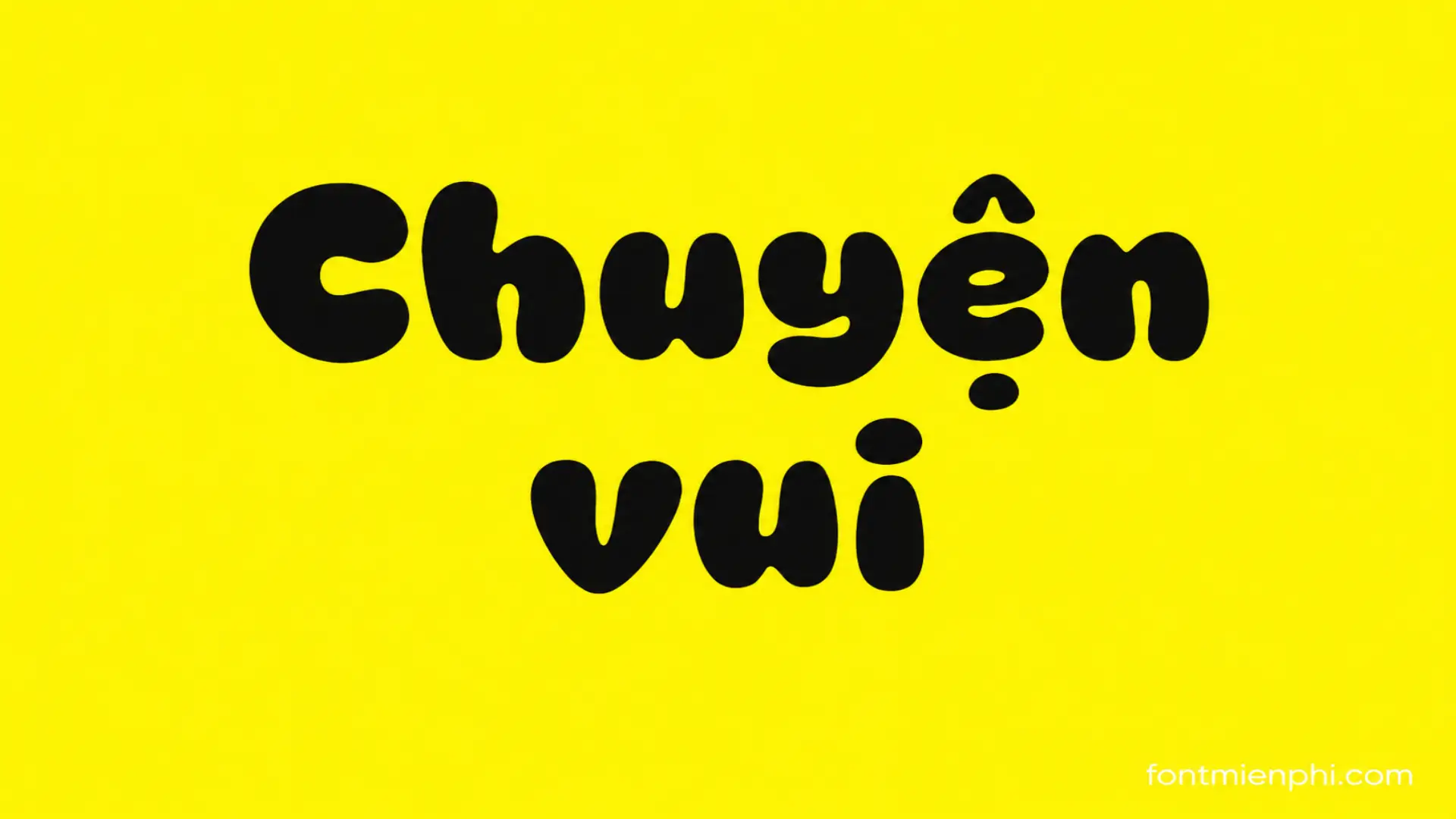
Tải Font Việt Hóa 1FTV VIP Super Kidpop – Phông Chữ Bầu Bĩnh, Siêu Dễ Thương Cho Thiết Kế
Chào mừng bạn đến với Fontmienphi.com! Nếu bạn đang tìm kiếm một phông chữ mang đậm nét trẻ trung, đáng yêu để “thổi hồn” vào các dự án thiết kế thì Font Việt hóa 1FTV VIP Super Kidpop chính là chân ái. Với phong cách to béo, ngộ nghĩnh, đây hiện là một trong những bộ font được giới Designer săn lùng và ứng dụng rộng rãi nhất.
1. Điểm nổi bật của Font Việt Hóa 1FTV VIP Super Kidpop
Không phải ngẫu nhiên mà 1FTV VIP Super Kidpop lại được xếp vào hàng ngũ các font chữ “quốc dân” cho phong cách thiết kế kẹo ngọt. Phông chữ này sở hữu những ưu điểm vượt trội:
• Thiết kế to béo, bầu bĩnh: Nét chữ dày dặn, bo tròn mềm mại tạo cảm giác cực kỳ thân thiện, vui nhộn và ngập tràn năng lượng tích cực.
• Việt hóa hoàn chỉnh: Từng dấu câu tiếng Việt được đội ngũ 1FTV chăm chút kỹ lưỡng, đảm bảo không bị gãy nét hay lỗi hiển thị khi gõ trên mọi phần mềm.
• Độ thu hút cao: Ngay cả khi đứng một mình, các ký tự của Super Kidpop cũng đủ sức làm nổi bật tiêu đề (Heading) mà không cần thêm quá nhiều hiệu ứng đồ họa phức tạp.
2. Ứng dụng đa năng trong thiết kế đồ họa  – Font Việt Hóa 1FTV VIP Super Kidpop
Với lợi thế về mặt thị giác, Font Việt hóa 1FTV VIP Super Kidpop là “vũ khí bí mật” giúp các thiết kế của bạn trở nên sống động hơn trong nhiều lĩnh vực:
🎨 Thiết kế cho Trẻ em (Kids & Babies)
Nhờ sự dễ thương vốn có, font chữ này cực kỳ hoàn hảo để làm bìa sách thiếu nhi, poster sự kiện vui chơi, banner quảng cáo đồ chơi, quần áo trẻ em hay các video hoạt hình, YouTube Kids.
🍔 Lĩnh vực Ẩm thực (F&B)
Nét chữ “mập mạp” tạo hiệu ứng kích thích vị giác rất tốt. Super Kidpop thường được ứng dụng để thiết kế menu quán ăn vặt, biển hiệu quán trà sữa, bánh ngọt, gà rán hoặc bao bì các loại snack.
📚 Giáo dục & Quảng cáo – Font Việt Hóa 1FTV VIP Super Kidpop
Trong các ấn phẩm giáo dục mầm non, tiểu học (flashcard, brochure trường học), việc sử dụng một font chữ dễ đọc, thân thiện sẽ giúp thu hút sự chú ý của các bé và phụ huynh một cách hiệu quả nhất.
3. Lợi ích khi sử dụng Font Super Kidpop
• Tối ưu khả năng đọc hiểu: Dù nét chữ khá dày nhưng khoảng cách (kerning) được tinh chỉnh cực tốt, giúp thông điệp truyền tải rõ ràng.
• Ghi dấu ấn thị giác: Thiết kế đẹp mắt, bắt trend, dễ dàng thu hút ánh nhìn của khách hàng mục tiêu.